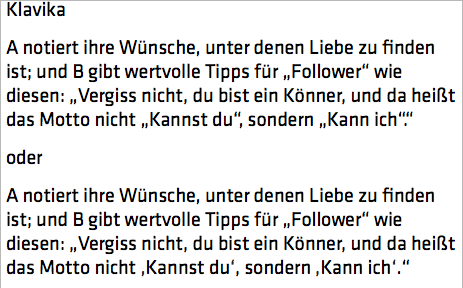
Anführungszeichen Ende: Wörtliche Rede im Zitat
Keine Suche in Google, in Foren oder im Duden liefern ein hilreiches Ergebnis. Vielleicht suche ich auch falsch, schlagt mich nicht, falls das schon  behandelt wurde.
Wir zitieren einfache, wörtliche Rede (ohne eigene Satzzeichen) innerhalb eines Zitats. Ist es richtig, dass am Ende " das Anführungszeichen die wörtliche Rede schlißt, ein Punkt folgt und das mit Anführungszeichen das Zitat beendet?
Je besser/teurer die Schrift, desto stärker unterschneidet die das automatisch.
XYZ gibt wertvolle Tipps wie diesen: „Vergiss nicht, du bist ein Leistungsträger, und da heißt das Motto nicht „morgen erledigen“, sondern „heute machen“.“
Der Duden listet hier einige Fälle, doch nicht diesen. https://www.duden.de/sprachwissen/rechtschreibregeln/anfuehrungszeichen
Ohne mich in der Frage absoluter formaler Korrektheit festlegen zu wollen: Was die Lesbarkeit angeht, sind die Beispiele mit einfachen versus doppelten An- und Abführungszeichen  den anderen deutlich überlegen.
Gibt es keine Vorgaben?
In den von mir betreuten geistes-/sprach- und rechtswissenschaftlichen Publikationen halten wir es immer so, dass innerhalb einer mit doppelten Anführungen markierten Rede dann die im Original wahrscheinlich auch doppelten Anführungen durch einfache ersetzt werden. Finde ich auch hübscher, ist aber wohl Geschmackssache.
Anders sieht es aus, wenn das Zitat als Ganzes deutlich durch Einrückung und/oder Abstände, kleinere Zeilenabstände oder kleineren Schriftgrad abgesetzt wird. Dann entfallen die äußeren doppelten Anführungen, da das Zitat als solches deutlich erkennbar ist, und die originalen doppelten Anführungen innerhalb des Zitats dürfen bleiben, wie sie sind.
Die (Edit: bei dir jeweils als zweite gezeigte) Variante wird dort überall favorisiert, auch bei den entsprechenden Verlagen (Peter Lang, Nomos, Harrassowitz, Köppe, Brill, V&R, de Gruyter, Akademie usw.).
Was die korrekte Anwendung einfacher und doppelter Anführungszeichen angeht, gibt der zitierte Duden-Link bereits Auskunft:
»Eine Anführung innerhalb einer Anführung wird durch halbe Anführungszeichen gekennzeichnet <§ 95>.«
Richtig ist also nur die Variante mit einfachen Anführungszeichen innerhalb der doppelten Anführungszeichen. (Ich kenne übrigens keine einzige geisteswissenschaftliche Publikation, die Variante 1 benutzt.)
Was die Unterschneidung angeht: Die Minion ist eine tolle Schrift. Aber die Unterschneidung von Anführungszeichen ist ein wirkliches Problem; man muss häufig (händisch) nacharbeiten, wenn es gut aussehen soll. Oder man benutzt alternativ französische Anführungszeichen »«.
Hmmnjoa, ich kenne leider welche ... manche Leute glauben einem nicht einmal, was im Duden steht, beharren auf Minuszeichen statt Spiegelstrichen, verbitten sich "diese komischen Zahlen" (Mediävalziffern) und korrekte diakritische Zeichen. Kannste nix machen, manchmal, wer zahlt, bestimmt, auch wenn's dann eben falsch ist.